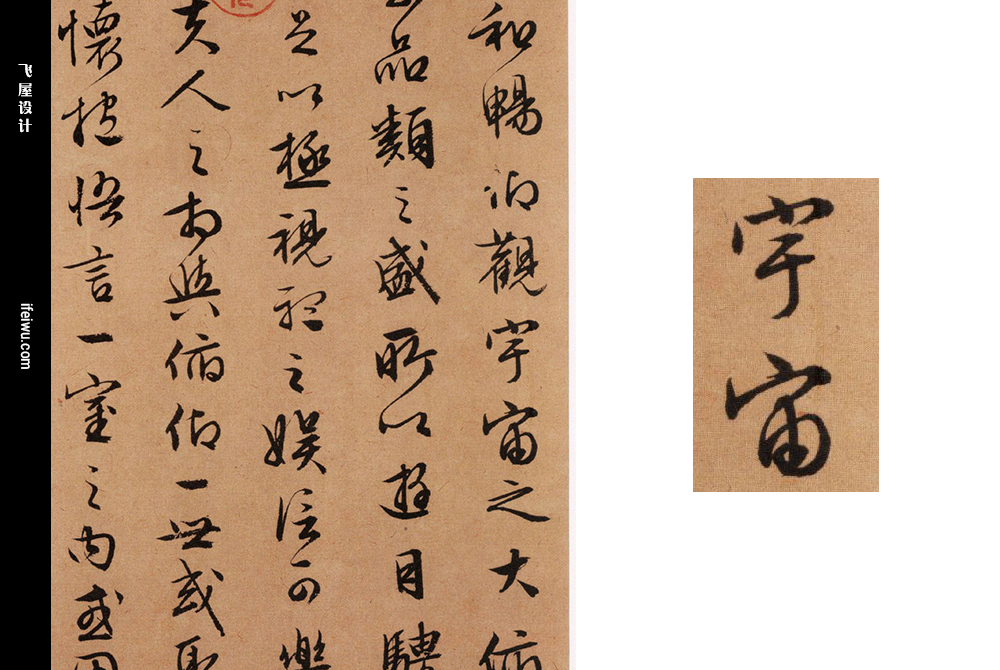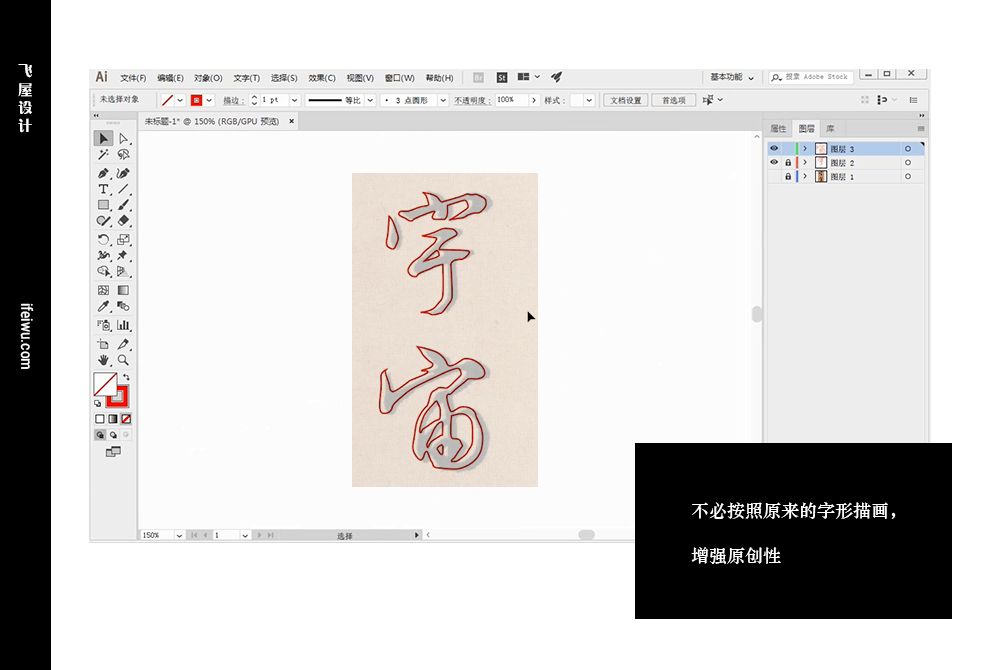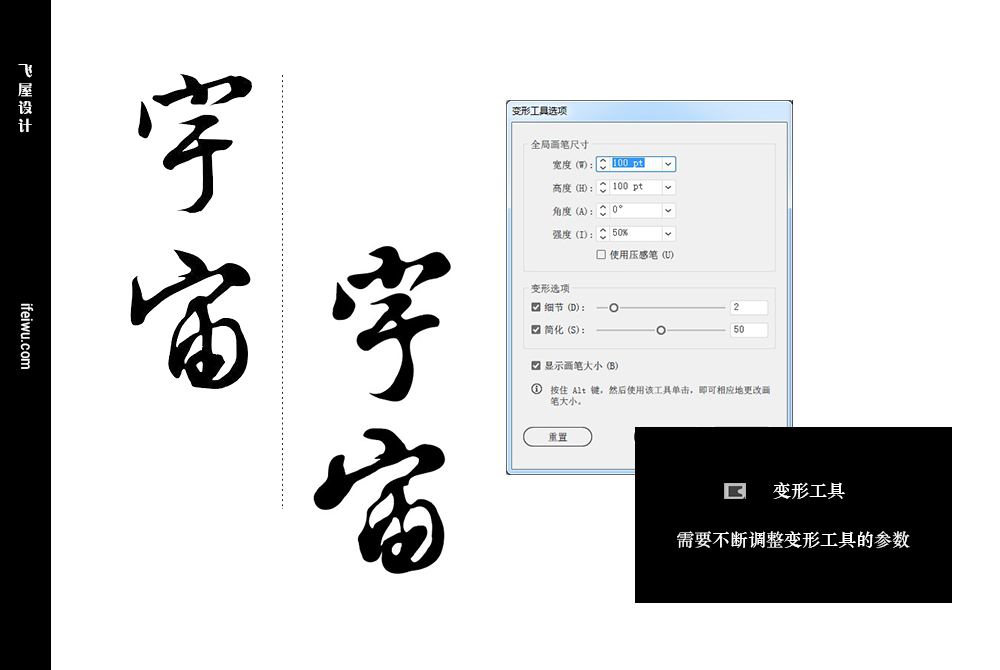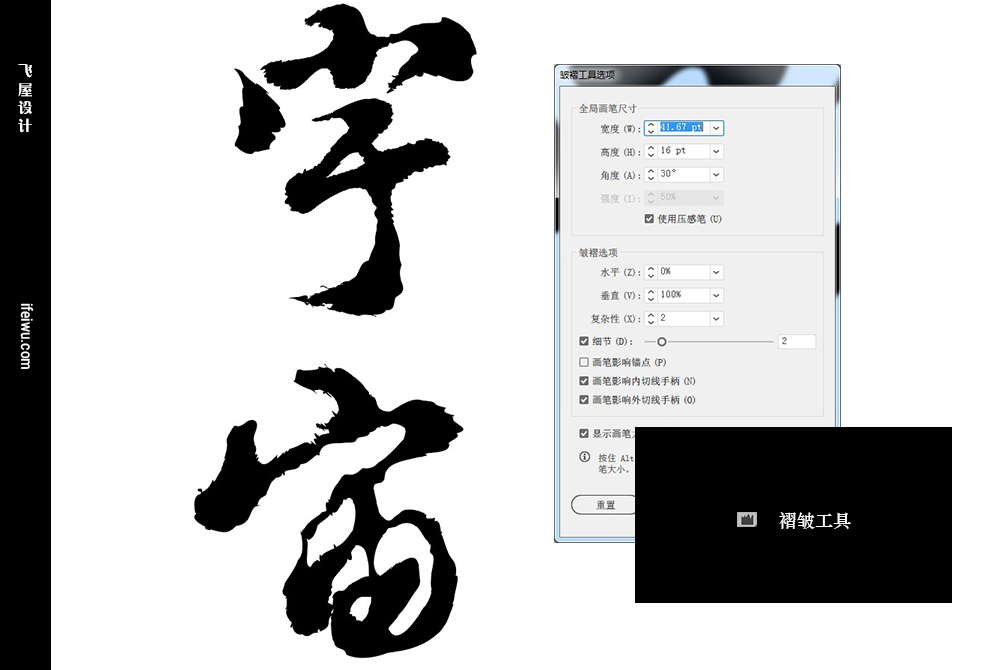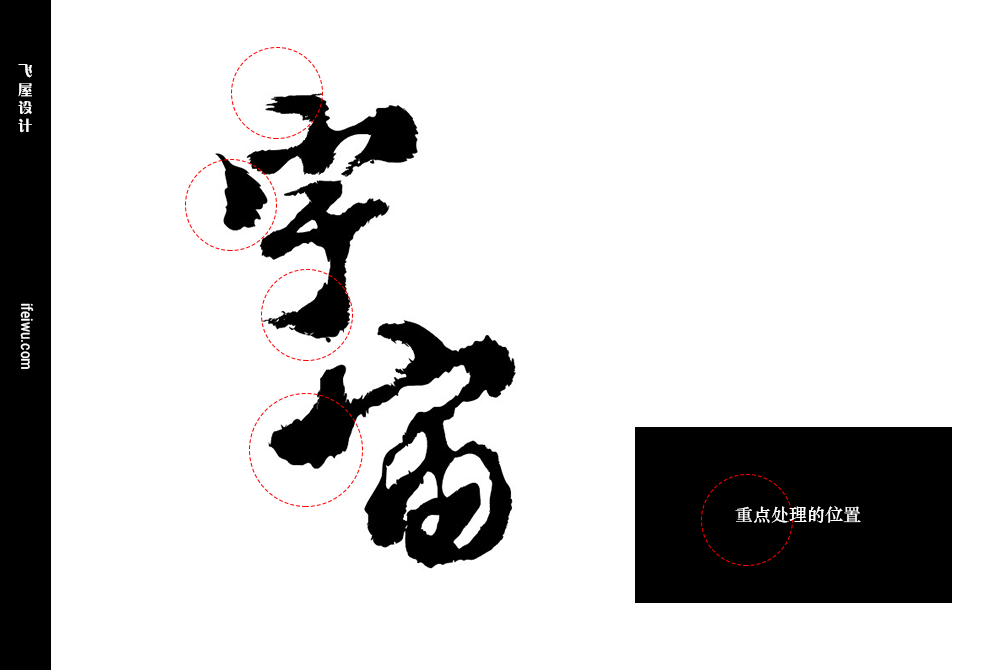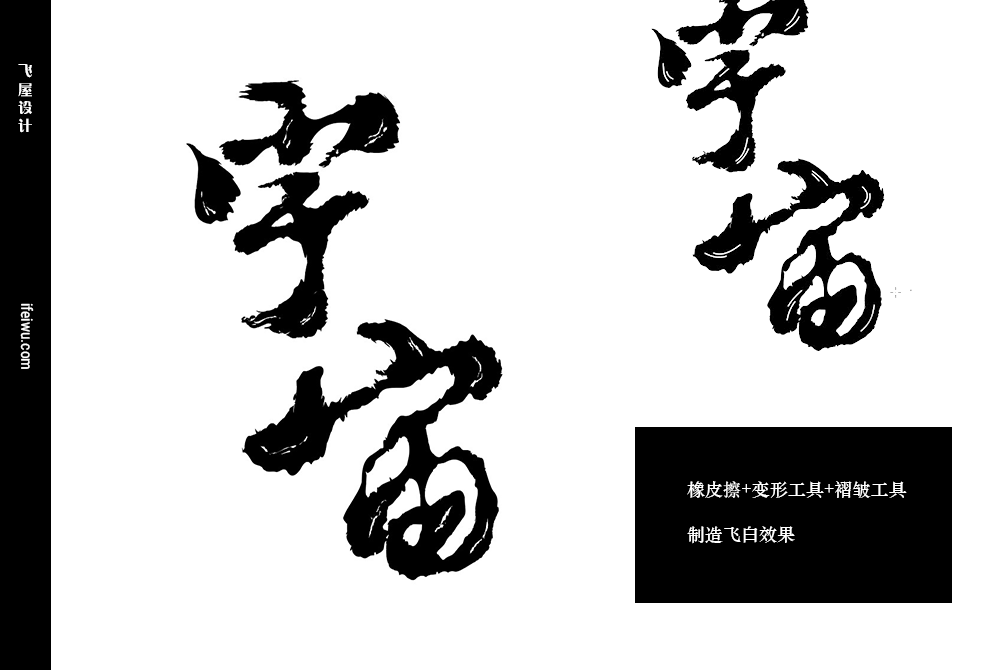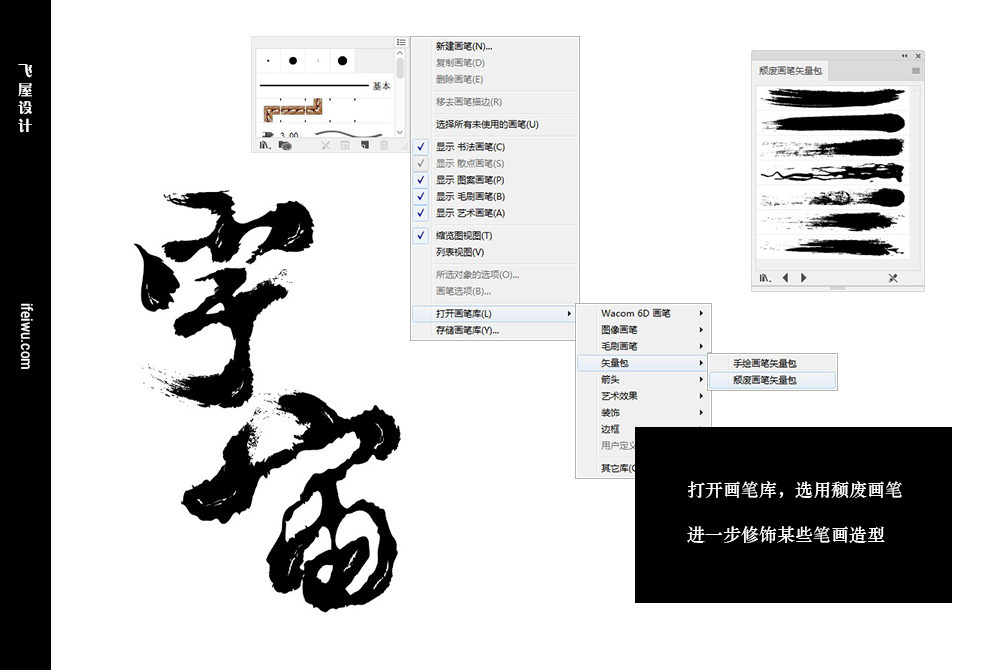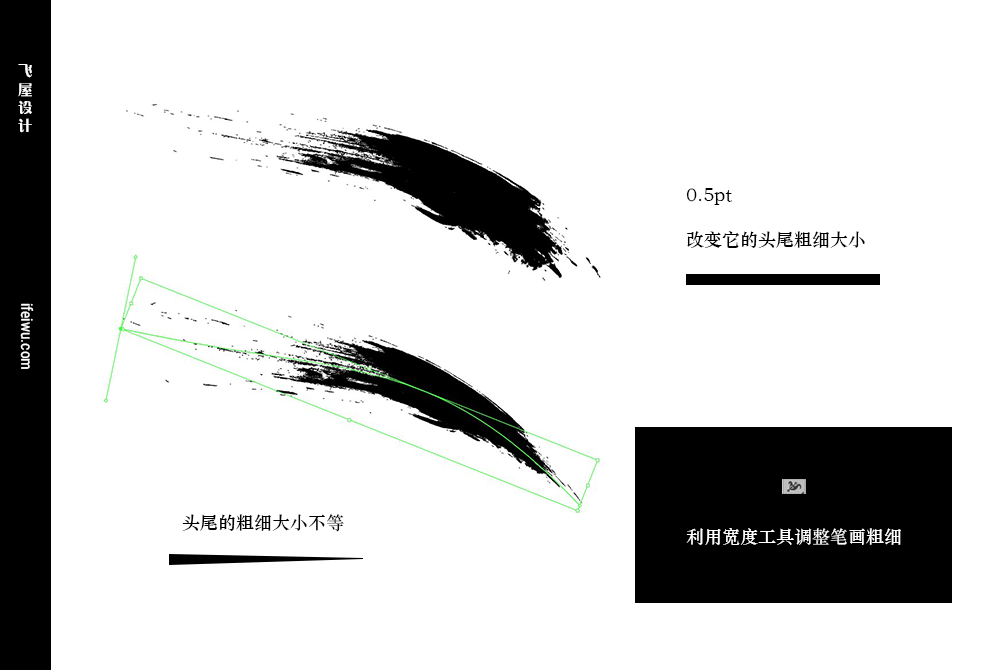
毛笔字体设计案例,用AI设计挥毫泼溅感毛笔字体
前言
对于毛笔的各种书体,虽然在网络里有许多书法类字体资源,但是试过后都会发现其效果并不十分理想。主要是由于东方书法的韵味有其自身运笔的独特性和它本身的不可复制性。如果我们能写出这样的字体当然是好事,但需要很长时间的精进磨砺。因此,今天我们就分享用AI设计挥毫泼溅感的毛笔字体的方法。
灵感来源
一个HK的设计师的分享视频,他提供了很多好的设计毛笔字体的方法,我在其中精选一些优秀的技巧,适当做了增删。
字形准备
STEP 01
书法的写法首先需要有一定的字形骨架。字形骨架有很多种搭建方式,在很多字体设计中都有介绍,我这里就不累述。毛笔的字形比较特殊,因此可以借助网络里的字体资源,选择比较适合的字体来开始,也可以从一些古代大书法家的作品里进行筛选。
我在这里选择的是明朝书法家文徽明的“行草《前后赤壁赋》”中的两个字“宇宙”来表现整个创作过程。他的书体造型生动,而且比较温婉有致。这里对于书体的选择,直接影响接下的设计。所以,如何开始即是个源头。
STEP 02
在新建的文档中将截选的这两个字拖入其中,并新建一个图层,锁定下方的图层。在新建图层上用钢笔工具描绘出字体的外形轮廓线。为了看得更清楚,这里可以关闭填充,只保留描边。
笔画的再变形
STEP 03
将字体的基本形状确定后,就可以将描边关闭,开启填充。开始对这个字形进行创作式的处理。第一个我们要使用的工具是“变形工具",变形工具可以改变路径对象的形状,根据你的操作来改变字体的外观。
这里的处理可以任意发挥,双击变形工具的小图标,将弹出出现变形工具选项的面板,对各种操作参数进行设置。这里最常用的是细节和简化。同时按住键盘上的ALT键使用鼠标的左右上下移动就可以改变工具大小,也可以在面板中进行参数调整。
这个过程让笔画可以稍微“圆润”一些。
STEP 04
我们将要使用“褶皱工具”对现有的笔画进行进一步处理,这一步将锋利平滑的笔画边缘调整为类似墨水浸润到宣纸上的那种泼溅质感。“褶皱工具”的使用最重要有两点,其一就是褶皱工具的大小,其二是褶皱工具的方向。也需要你在创作过程中不断更换这些属性,以便根据实际情况作出调整。
虽然是变形处理,但也要遵循书法本身的书写规律,这必定需要设计师对毛笔的运笔有一些了解。(广泛涉猎,没有坏处~)
STEP 05
对于目前的字体仍然不满意,可以继续采用褶皱工具和变形工具一起处理。这里如果对褶皱工具和变形工具进一步做“夸张”的调整。如果在方向上不好把握,还可以通过调整字体的方向来让操作变得更容易。
在字体的位置和大小也可以进行一定的改变,以适应我们的造型布局。
润色造型
为了让字形显得更为个性,增强其魅力,还可以做以下的处理。
STEP 06
为笔画增加一些毛笔的“飞白”,这里可以用上“橡皮擦”工具。橡皮擦大小可以根据字体进行调整,目的是在这里制造一些空白,然后再用褶皱工具和变形工具改变这些空白的造型,使其变得更为自然生动。
STEP 07
对于字形里的某些笔画,还可以采用画笔工具“画”出这些笔画特殊造型。这里的画笔需要打开画笔面板右上角的图标,【打开画笔库>矢量包>颓废画笔矢量包】,在这个画笔库里有很多可选择的能用来修饰笔画的艺术画笔。
你还可以调整画笔的粗细大小以适应你的整体结构需要。一个笔画可以利用宽度工具对不同的笔画进行调整。
STEP 08
最后将上一步所添加的笔画进行扩展外观,并和原有的笔画进行合并。这里需要注意的是,扩展外观后的笔画会留有空白的边框,这个边框也是一个路径对象,这里需要将它选中并删除,才能和原有笔画进行合并。
此外为字体继续添加一些墨点,以还原得更加真实。仍然采用画笔,打开画笔库中的【油墨】艺术画笔。能胜任墨点的有哪些笔刷,我们一目了然。在完成墨点造型后,将这些墨点进一步扩展并填充与字体一样的颜色,因为这些油墨的艺术画笔本身的色彩并不完全是纯黑。
最终效果
这里我采用渐变叠加,展示最终的效果。